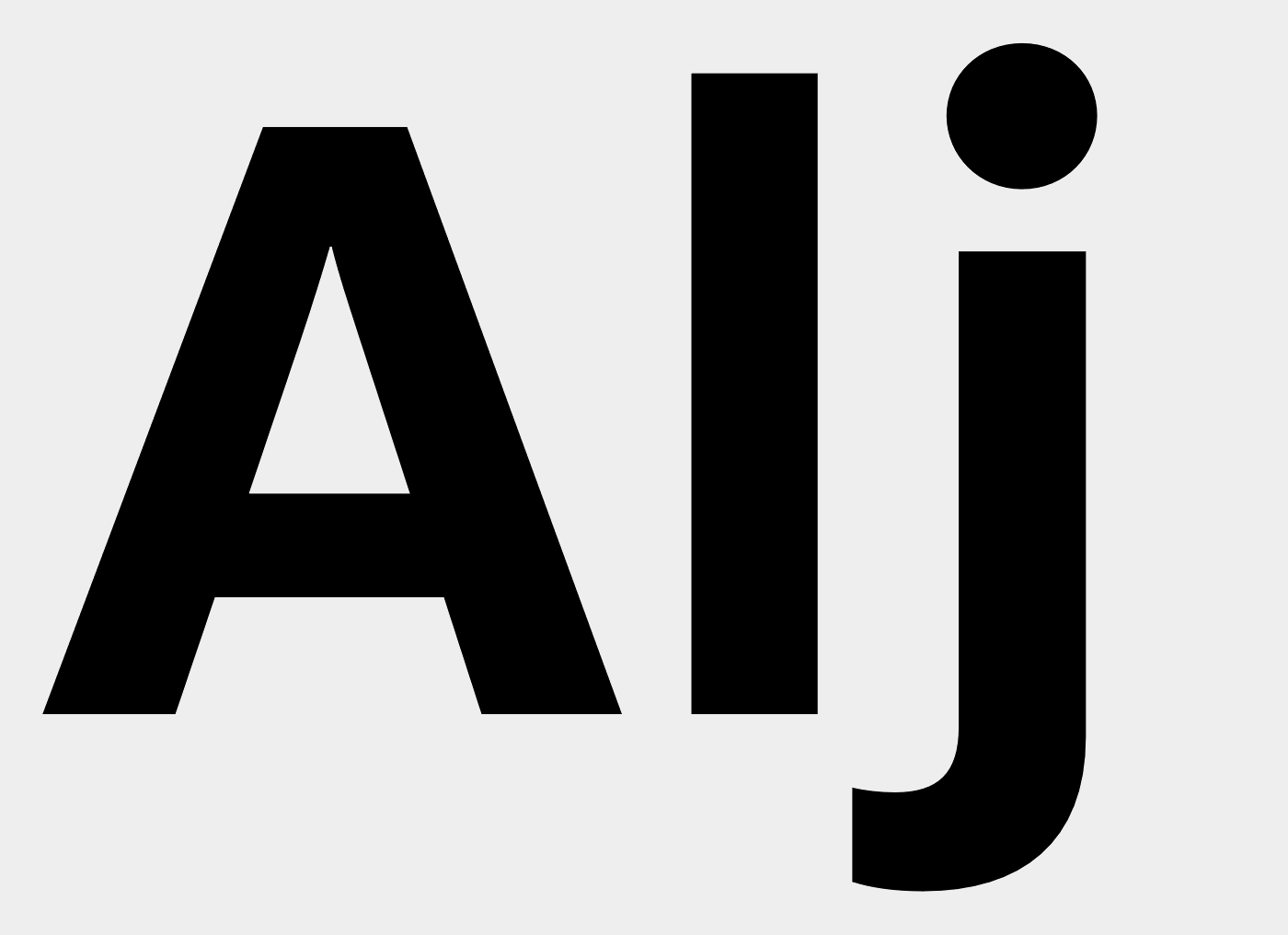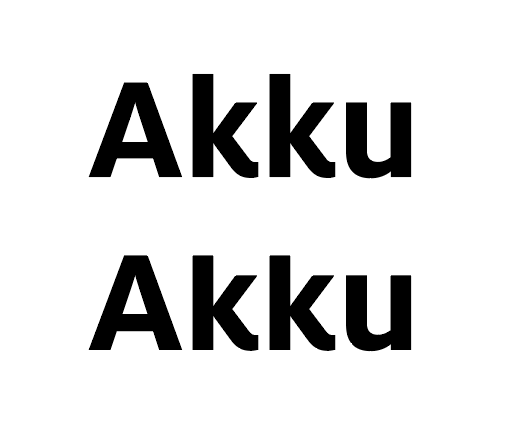
Überhang entfernen für Logo
macht es Sinn den Überhang von Buchstaben einer Wortmarke zu entfernen (hier k)?
Ich finde es trägt zur Kompaktheit bei, allerdings irgendwie auch abgeschnitten.
Was meint ihr?
Der eine sieht’s so, der andere anders … Für mich sehen die neuen Oberlängen des k optisch zu kurz aus, im Original sind sie mir zu lang. Wenn nur wenige Buchstaben aus einer Satzschrift herausgenommen und für ein Logo verwendet werden, ist das immer mit Handarbeit verbunden, weil die sich in den seltensten Fällen harmonisch zusammenfügen. Was ein ganzer Text an gewollter optischer Ruhe bietet, bieten eben drei zufällige Buchstaben nicht.
Wenn ich beispielsweise einen Alj als Kunden hätte und die Milo als Logofont verwenden wollte, würde ich das auch nicht einfach so stehen lassen, weil das noch kein Logo ergibt: